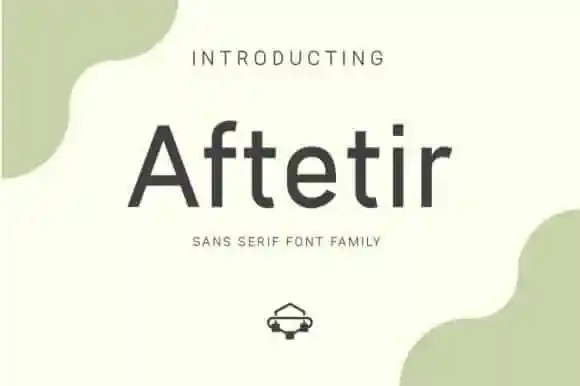
Aftetir Sans Serif é uma elegante tipografia sans serif criada por AmruID, disponível para download pela 99designs. Com seu design minimalista e versátil, esta fonte oferece um leque de estilos que vão desde o texto principal até grandes headlines, combinando elementos clássicos com designs modernos e carregados de impacto. Perfeita para projetos criativos em geral, Aftetir tem a capacidade única de transformar seus ideais artísticos num nível elevado, tornando-se uma fonte verdadeiramente amada. Ideal tanto para aplicativos online quanto impressão, essa fonte é perfeita para quem busca um equilíbrio entre simplicidade e expressividade. Combinada com outras fontes ou usada sozinha em projetos de design gráfico, Aftetir é uma escolha confiável que não apenas vai trazer seu projeto à vida, mas também o deixará impressionado por sua capacidade única de adaptar-se a um vasto leque de estilos.